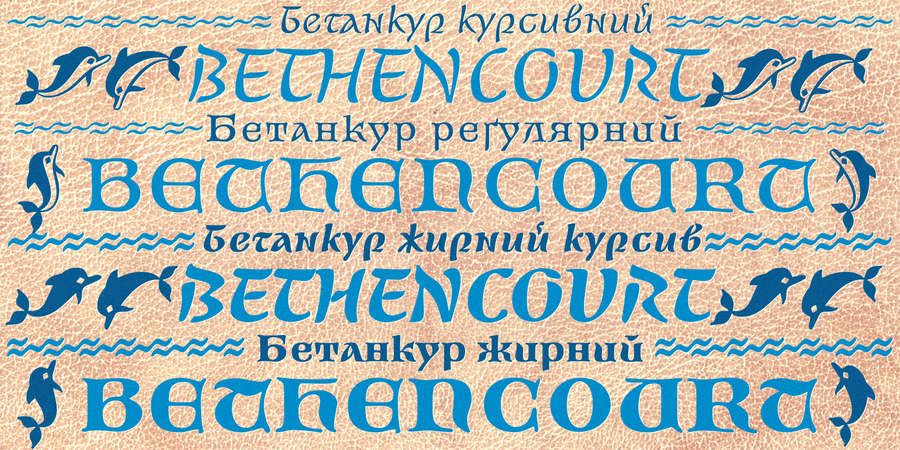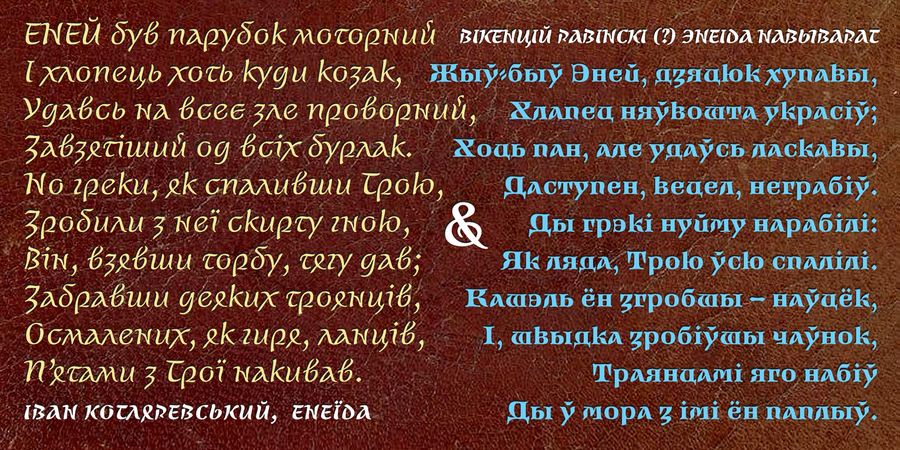
Цей шрифт з’явився завдяки замовленню старого клієнта Всеволода Буравченко, що займається реконструкцією старовинних навігаційних приладів. З оцифрованного в Автокаді історичного унціалу треба було зробити повноцінний шрифт. Потім вирішили додати повний комплект знаків і накреслень, тим паче, тема кирилічного унціалу майже не розроблена, хоча це перше суто книжкове латинське письмо, яким користувалася вся християнська Західна Європа аж до Британських островів. Знайшлися відповідні прототипи, наприклад, прописний унціал, що склався та активно вживався у 4-5 століттях, та ще довго по тому, в якості ініціалів для готики, найвідоміший під назвою «ломбардські версали» З 6 століття під впливом курсиву все більша кількість виносних елементів, що, як вважається, полегшує та прискорює читання, перетворила унціал на півунціал – перший прототип прямого мінускулу. Іншим аналогом став римський курсив, що має давню історію (приблизно з 1 ст. н. е.), ним писали на воскових табличках, що зумовило спрощену форму літер. Початково так званий старий римський курсив мав маюскульну форму, але розвиваючись набув виносних елементів, перетворившись на новий римський курсив. У ньому власне вперше й виникли мінускульні форми, що вплинули як на характерні особливості унціалу і півунцалу, так і на формування деяких місцевих видів письма: візиготського на Піренейському півострові, беневентинського на півдні Італії або меровінґського на півночі Франції. Якщо унціал та півунціал хоч якось втілені у сучасних фонтах, римські курсиви, здається, взагалі не розроблялися – тим цікавіше було адаптувати їх під сучасне розуміння графем та втілювати в кирилиці. Всі накреслення напрочуд легко та приємно читаються навіть у суцільному тексті. Bethencourt добре працює як самостійно, так і в сполученнях із ренесанс-антиквами, курсивами широкого пера, іншими унціалами та півунціалами, готикою. Шрифт розробив Віктор Харик у 2020 році.